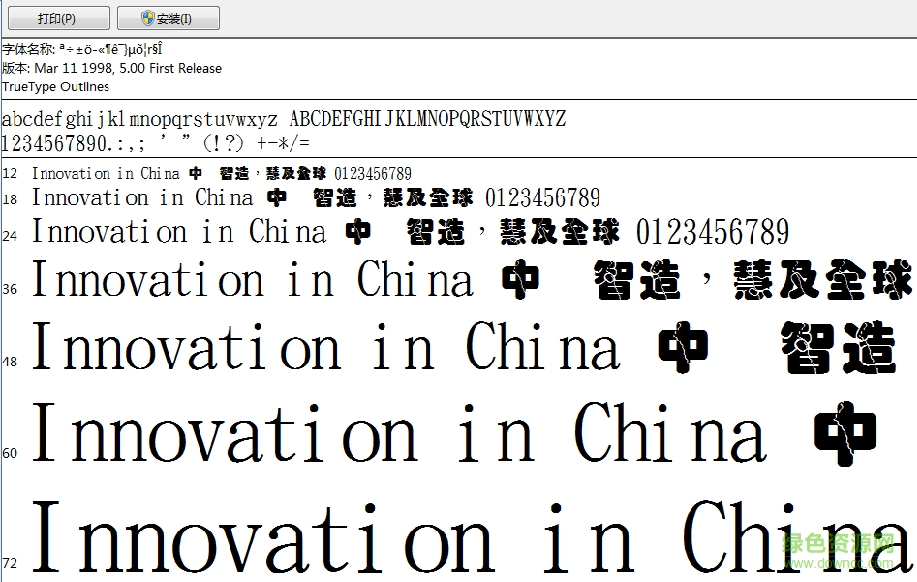
金梅重圓破裂字形
金梅重圓破裂字體金梅字體庫的一種個性字體,常應用于廣告設(shè)計,廣告創(chuàng)意、雜志報刊、印刷制作等行業(yè),非常的實用,還能隨心的更換喜歡的造型設(shè)計。喜歡就來綠色資源網(wǎng)下載吧!
金梅重圓破裂字體特色
獨特字體,隨心而換
話題字體,潮流設(shè)計